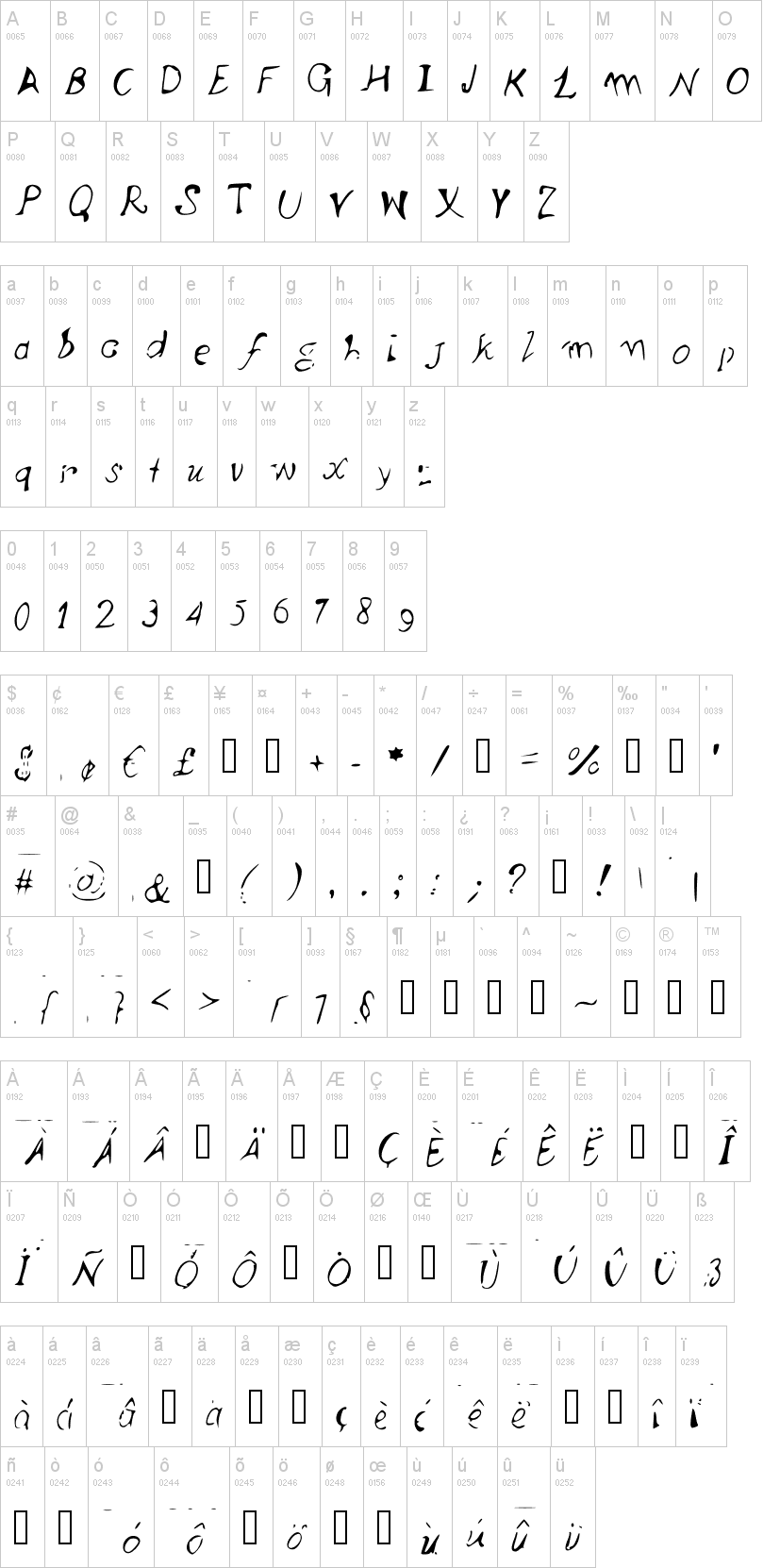
? Argento e Berlio 字体是一种现代意大利文字体,由设计师Alessandro Segalini设计。它具有非常优雅的外观,具有良好的可读性和可视性,可以用于多种应用,包括印刷材料、网页和平面设计。它的字母形状具有柔和的曲线,而字体的整体外观则更加强调了字母的清晰度和可读性。它的字体风格既适合印刷材料,也适合网页和平面设计,因此可以用于各种应用场景。内容介绍
Argento e Ber lio是一款非常不错的手写艺术字体,具有很好的视觉感,适合于文化类的宣传设计、商业类品牌的广告和产品包装设计以及个性化文字排版等较多场景。